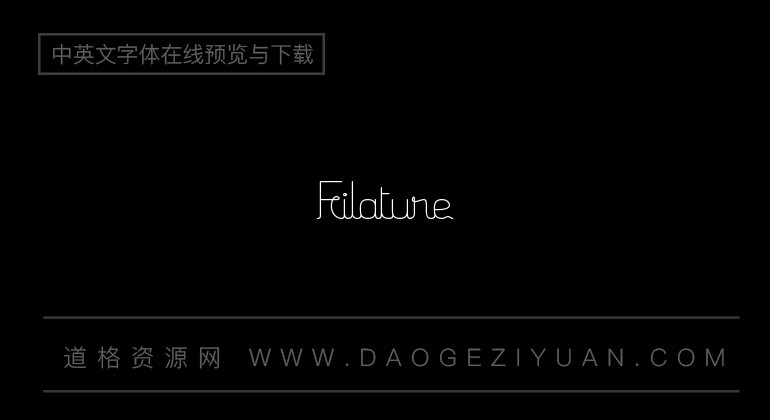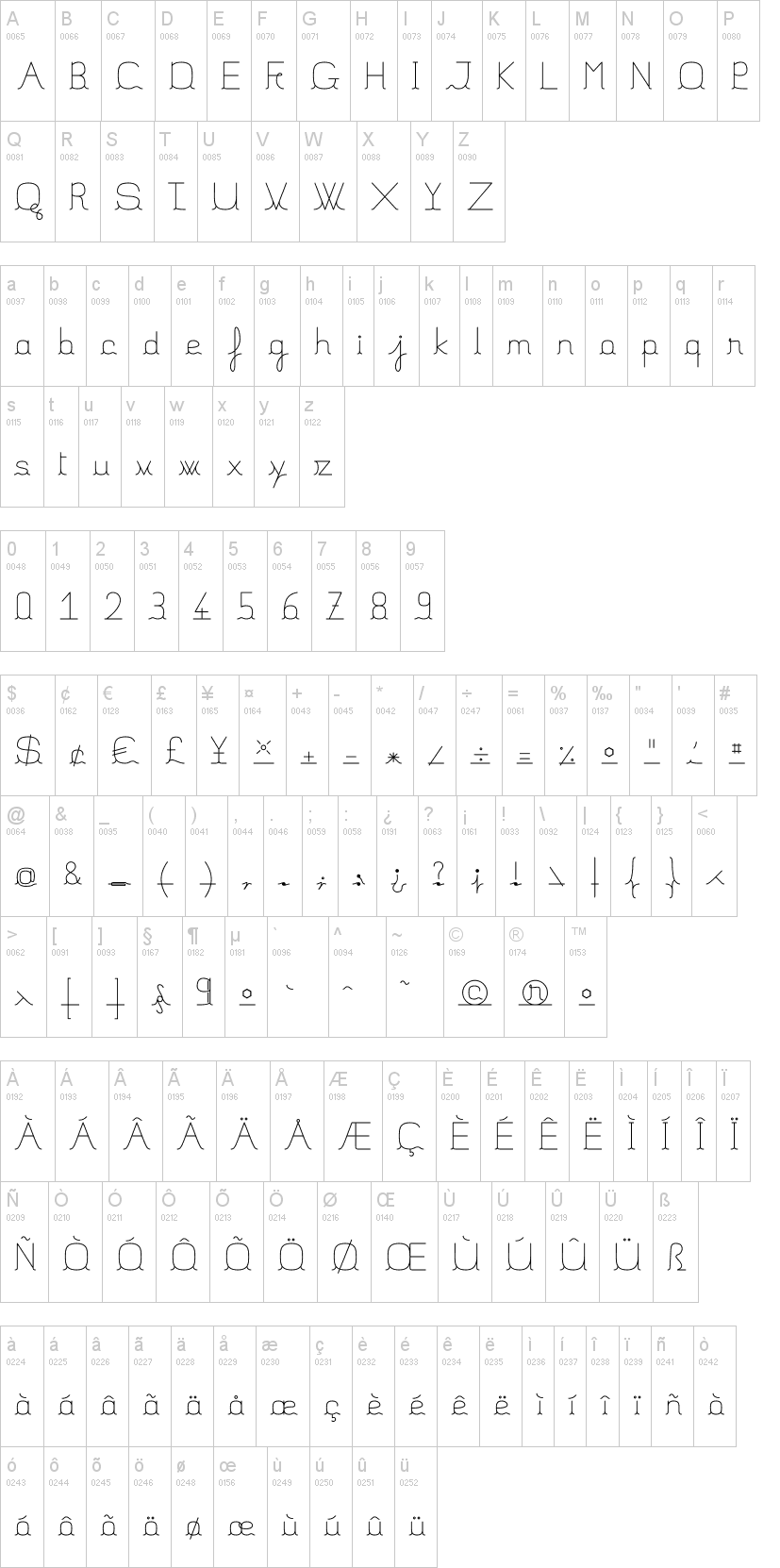
Filature 是一款现代派的脚本字体,它的设计者是著名的荷兰字体设计师 Martin Majoor。它的主要特点是字母的曲线简洁优雅,字体的设计风格清新自然,给人一种温柔的感觉。Filature 字体可以用来创作精致的文字效果,也可以用于创作报纸、杂志等印刷作品,它的设计风格可以让文字的表达更加丰富多彩。内容介绍
Filature是一款非常不错的手写艺术字体,具有很好的视觉感,适合于文化类的宣传设计、商业类品牌的广告和产品包装设计以及个性化文字排版等较多场景。